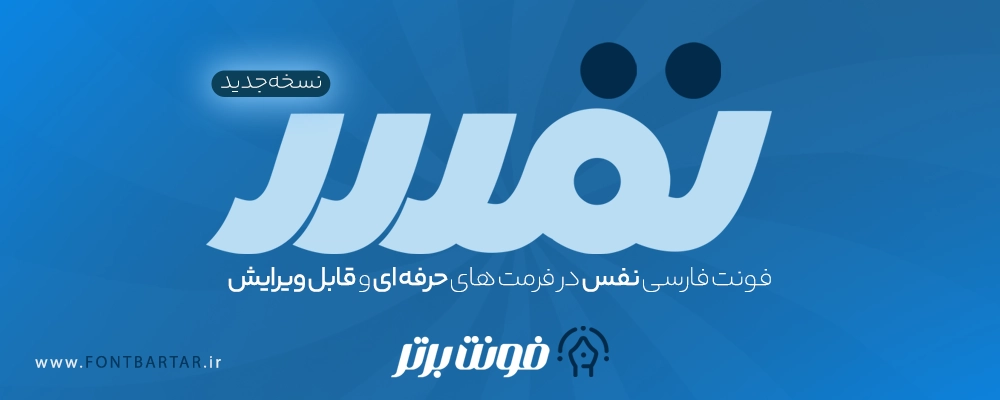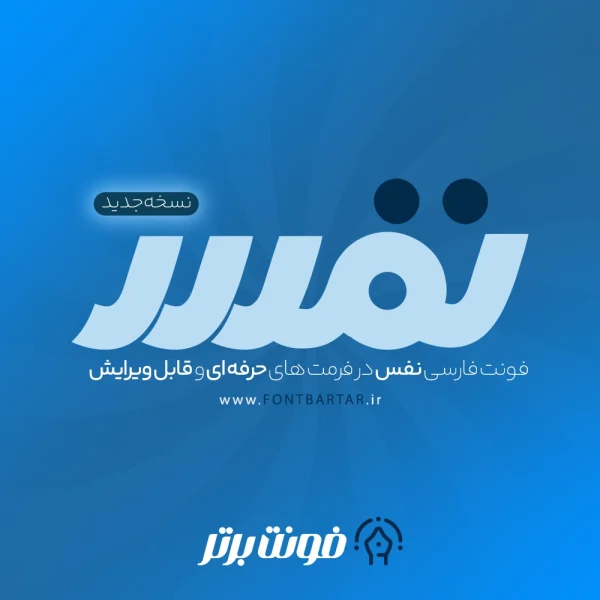
فونت فارسی نفس
Nafas Font
فونت نفس یکی دیگر از فونت های طراحی لوگوتایپ و تایپوگرافی می باشد، فونت فارسی لوگو نفس با طراحی حرفه ای و انعطاف پذیر می باشد و این امکان را فراهم می آورد که به راحتی بتوانید حروف را در کنار هم قرار دهید، با خرید فونت فارسی نفس می توانید بدون هیچگونه دانشی لوگو تایپ طراحی کرده و تایپوگرافی های زیبایی انجام دهید و از آن کسب درآمد کنید.
فونت نفس بر خلاف سایر فونت ها به صورت لایه باز بوده (psd) و امکان تایپ مستقیم در نرم افزار ها را ندارد همچنین شامل تمامی حروف از الف تا ی می شود این فونت به چینش های مختلف می تواند در کمترین زمان این امکان را به طراح بدهد که یک لوگو تایپ حرفه ای برای کسب و کار های مختلف طراحی کند ویژگی های این فونت حرفه ای را باهم مرور کنیم.
مزایای استفاده از فونت فارسی لوگو نفس :
• تمامی حروف به صورت لایه باز
• ویرایش آسان حروف
• طراحی لوگوتایپ
• طراحی لوگو به صورت آسان و بدون هیچگونه آموزش
• شامل تمامی حروف از الف تا ی در تمامی حالت ها
فونت لوگوتایپ نفس